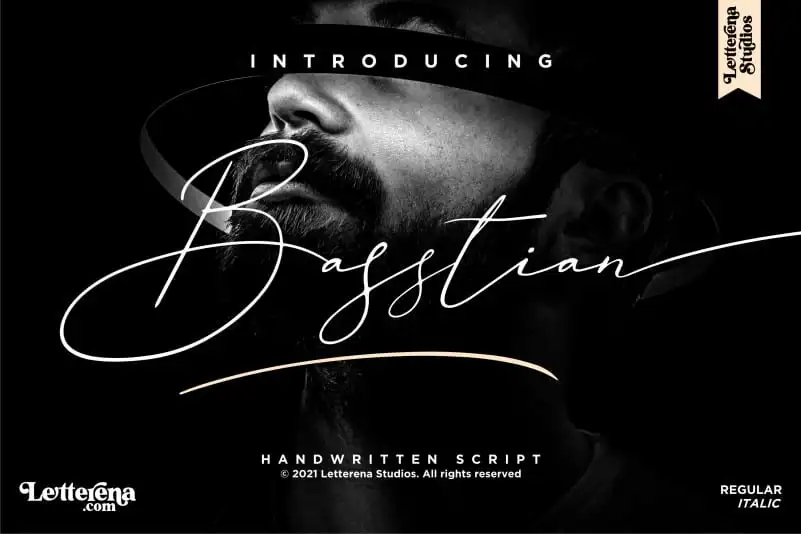
Basstian Handwritten Font – Download Grátis
A Basstian Handwritten Font é uma escolha perfeita para designers que procuram adicionar um toque autêntico e sofisticado a seus projetos digitais ou impressos. Desenvolvida pela Letterena, esta fonte de escrita cursiva é ideal para criar identidades visuais memoráveis, como logomarcas e embalagens de produtos, bem como designs em homenagens pessoais como cartões de visita, convites e presentes personalizados. Além disso, ela se adequa perfeitamente a criações gráficas detalhadas como posteres, mugs e até mesmo ao fazer a marcação em fotografias ou para criar um toque especial em eventos especiais. Com seu charme único, a Basstian Handwritten Font é uma ótima opção para aqueles que buscam dar um toque autêntico aos seus projetos de design.